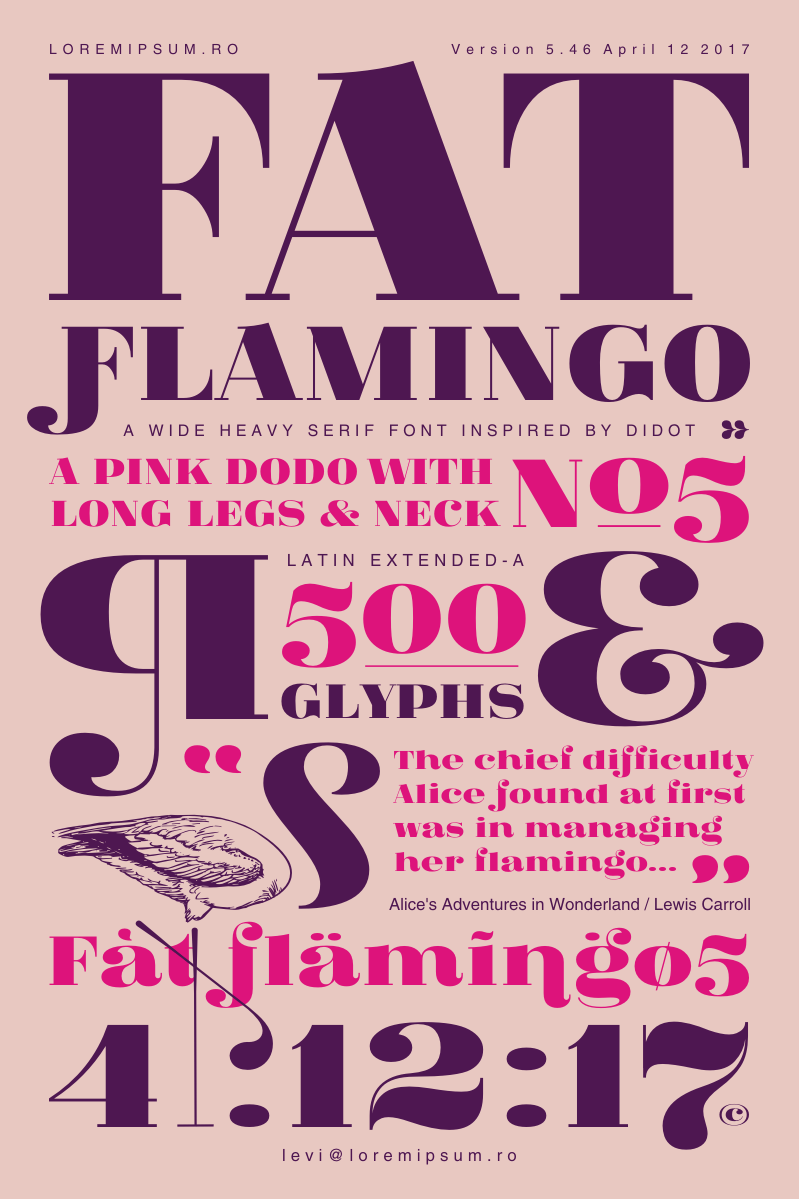
Aqui está uma versão para português do Brasil de 2 parágrafos curtos sobre a fonte “Fat Flamingo 5 Font”, com foco em ser informativo e convidativo, similar ao tom de um blog de recursos gráficos: Sintaxe: Serif Fonts. O desenho elegante e detalhado da Fat Flamingo 5 Font vai dar seu design uma presença única na tela digital ou impressa. Conhecida pelo designer Levi Szekes, a Fat Flamingo 5 oferece linhas finas com acabamento suave e captações meticulosamente trabalhadas para criar um olhar atraente e sofisticado. Perfeita para gráficos profissionais, logotipos de empresas ou materiais de marketing, esta fonte é uma escolha ótima se você deseja dar seu trabalho um visual impecável. Esta font pertence ao catálogo de fonts da Archive, sendo um recurso raro e valioso para designers que desejam explorar novas possibilidades de design. Se você está buscando criar algo atraente sem comprometer o profissionalismo, Fat Flamingo 5 é uma escolha inteligente para sua coleção de recursos gráficos.
Designer: Levi Szekeres